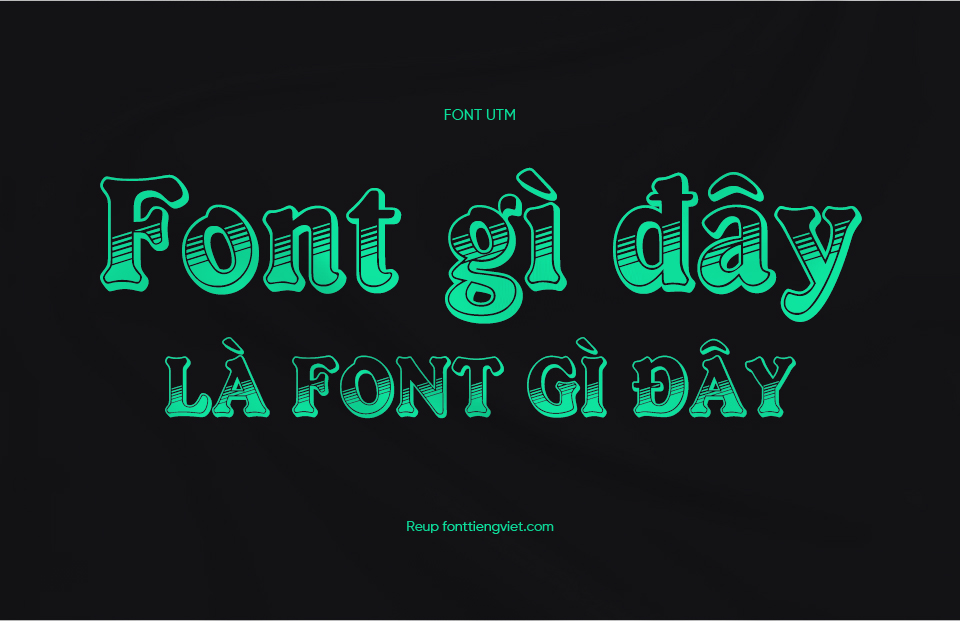
Giới thiệu về Font việt hóa UTM Cabaret
Trong cộng đồng thiết kế đồ họa tại Việt Nam, việc lựa chọn một Font Miễn Phí chất lượng luôn là ưu tiên hàng đầu của các bạn trẻ. Một trong những cái tên nổi bật nhất chính là Font việt hóa UTM Cabaret. Đây là một phông chữ thuộc bộ UTM nổi tiếng, mang phong cách cổ điển, quý phái nhưng không kém phần hiện đại. Với những đường nét cách điệu tinh tế, font chữ này thường được các bạn học sinh, sinh viên sử dụng để trang trí báo tường, làm slide bài thuyết trình hoặc thiết kế các ấn phẩm văn hóa nghệ thuật trong nhà trường.
Đặc điểm nổi bật của phông chữ
Lý do khiến Font việt hóa UTM Cabaret trở nên phổ biến chính là sự linh hoạt trong ứng dụng. Phông chữ sở hữu độ dày vừa phải, các góc cạnh được bo tròn nhẹ nhàng tạo cảm giác thân thiện và dễ nhìn. Đặc biệt, bản việt hóa đã được tối ưu hoàn toàn các dấu tiếng Việt, giúp người dùng không còn lo lắng về lỗi hiển thị ký tự khi gõ văn bản trên các phần mềm như Photoshop hay Canva. Bạn có thể dùng nó để tạo điểm nhấn cho tiêu đề hoặc làm logo cho các câu lạc bộ học thuật.